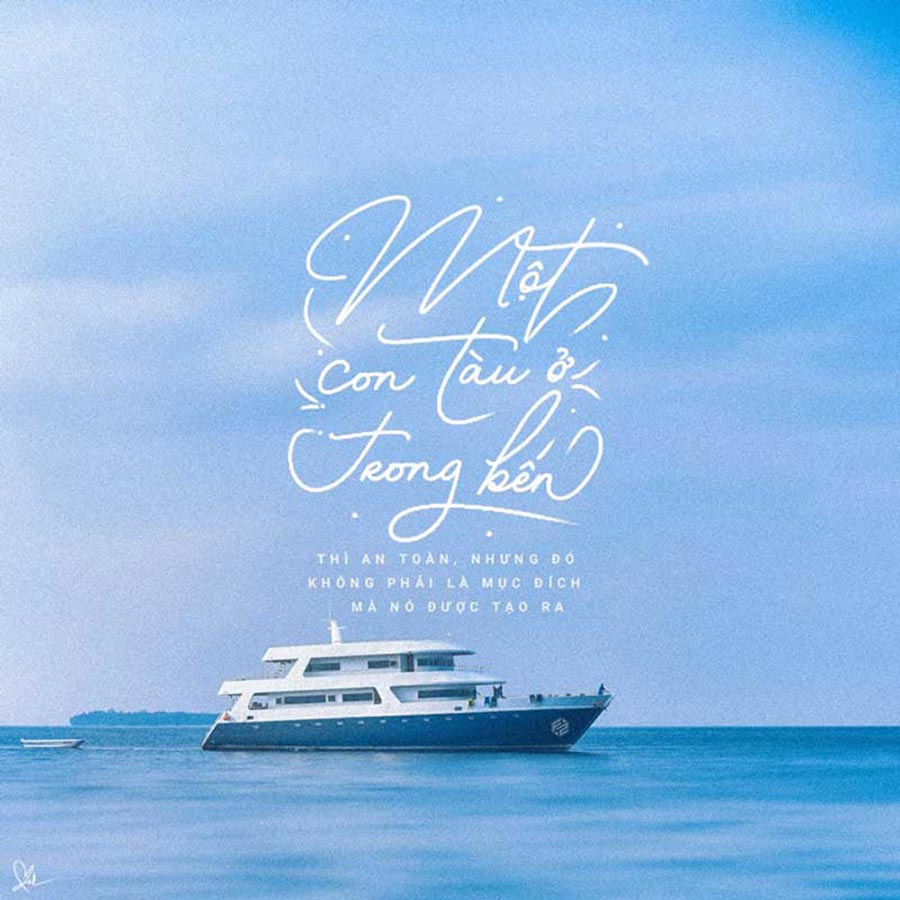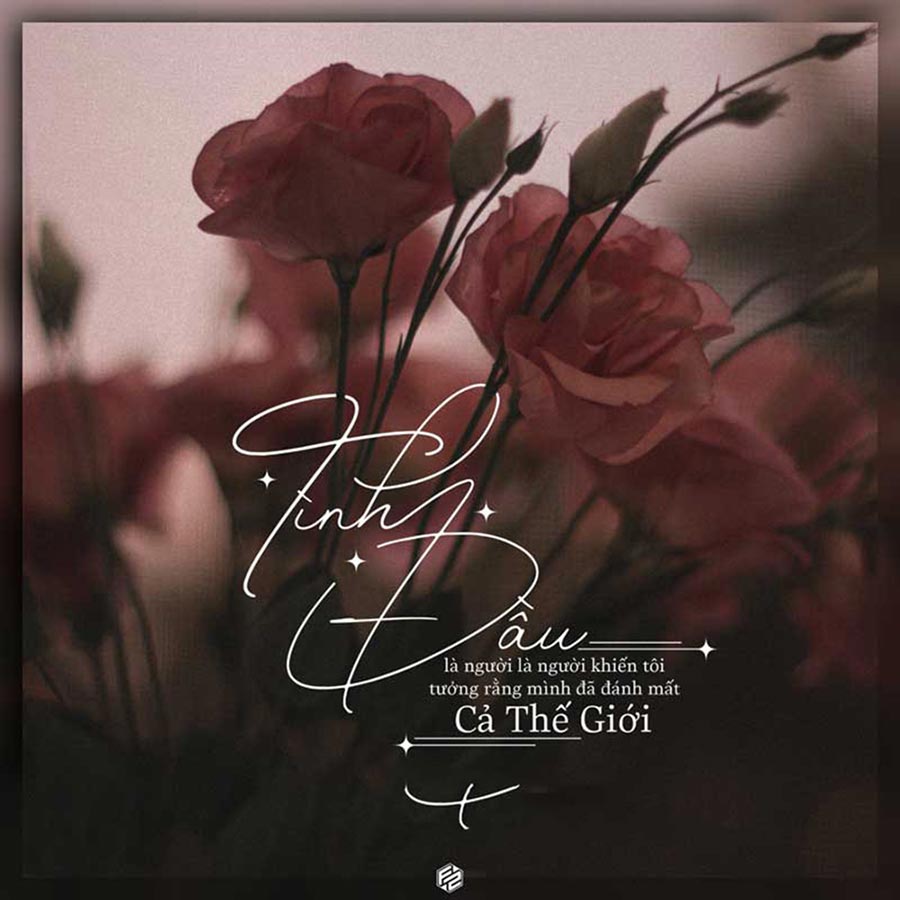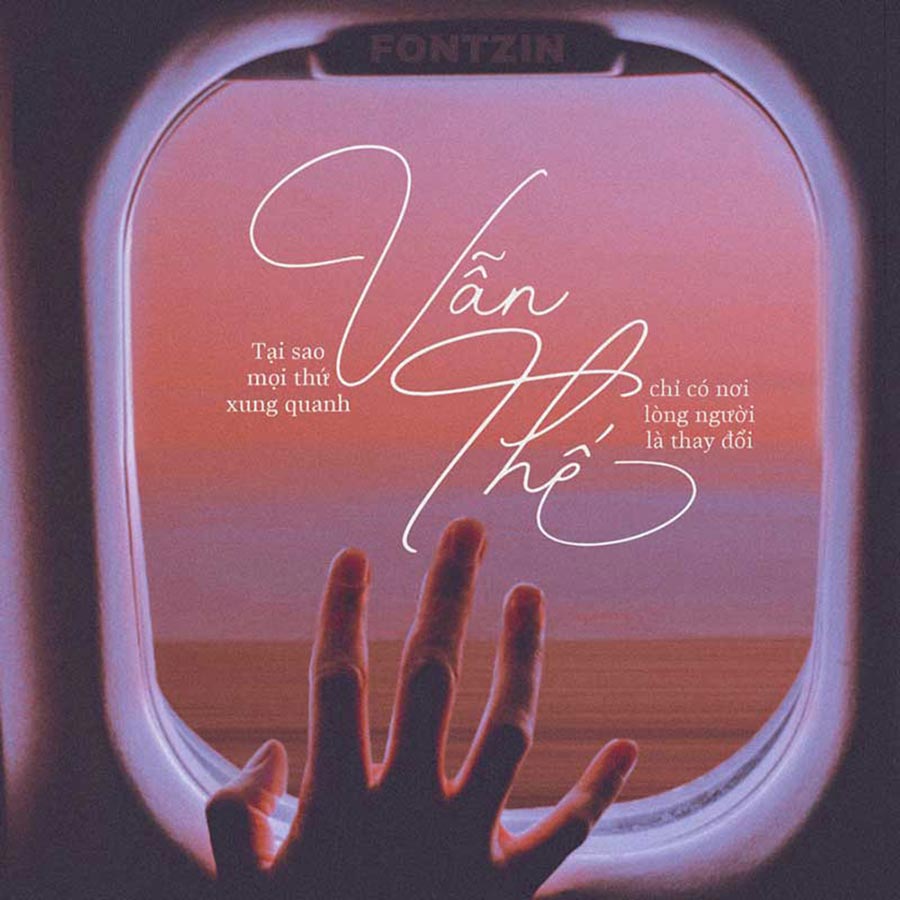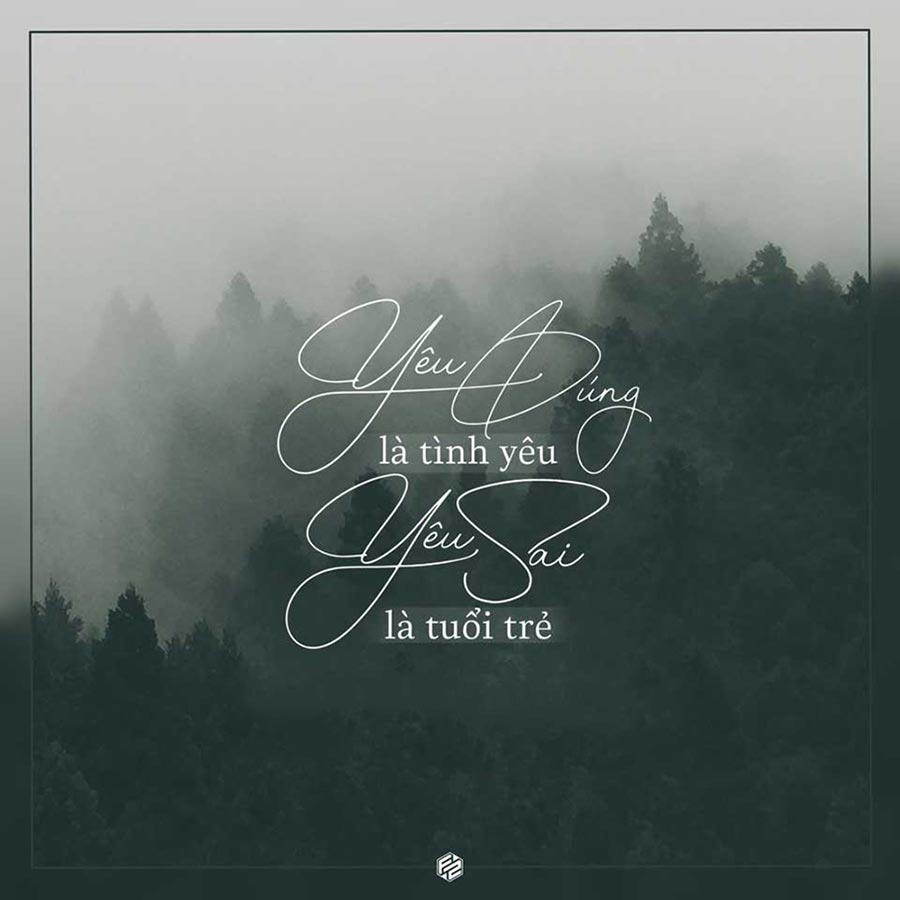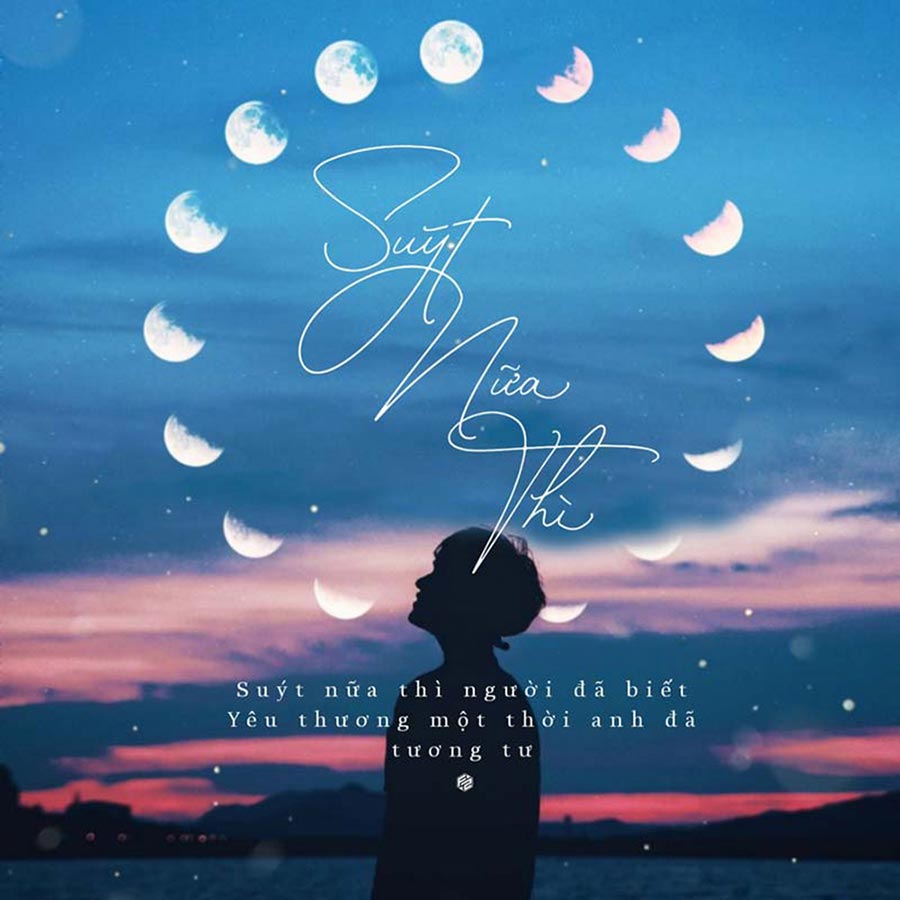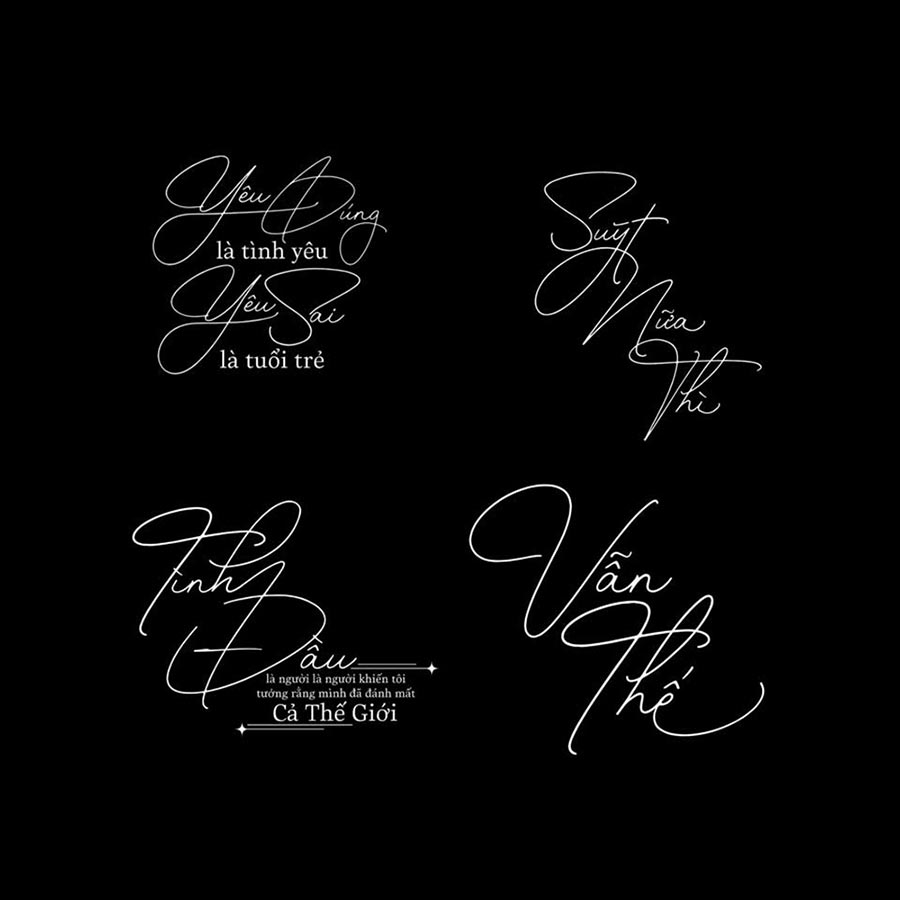
Chia Sẻ Miễn Phí Font Việt Hóa - The Handwritten Watermark Font Chữ Ký Siêu Đẹp
Trong thiết kế đồ họa, việc lựa chọn font chữ là một yếu tố quan trọng, giúp định hình phong cách và truyền tải thông điệp hiệu quả. The Handwritten Watermark Font là một font chữ mang đậm dấu ấn cá nhân, với vẻ đẹp mềm mại và tinh tế, tạo cảm giác như những chữ ký tay chân thực. Đặc biệt, phiên bản Việt hóa của font chữ này đã được chia sẻ miễn phí cho cộng đồng thiết kế, mang đến cơ hội cho mọi nhà thiết kế, từ những người mới bắt đầu đến các chuyên gia, sở hữu một công cụ tuyệt vời để nâng cao chất lượng công việc sáng tạo của mình.
1. Phong Cách Chữ Ký Tinh Tế và Sang Trọng
Font The Handwritten Watermark Font được thiết kế với phong cách chữ ký tự nhiên, mềm mại và tinh tế, giống như nét chữ được viết tay trên giấy. Với các đường cong uyển chuyển và sự kết hợp giữa các ký tự thanh thoát, font chữ này mang lại cảm giác sang trọng và độc đáo. Nó rất phù hợp cho các thiết kế cần sự tinh tế, như thiệp cưới, chữ ký số, logo thương hiệu, và các dự án thiết kế cá nhân hóa. Sự mềm mại của các nét chữ sẽ giúp các sản phẩm thiết kế trở nên gần gũi, lãng mạn nhưng không kém phần trang nhã.
2. Việt Hóa Hoàn Hảo Cho Dự Án Thiết Kế Tiếng Việt
Một trong những điểm đáng chú ý của The Handwritten Watermark Font là phiên bản Việt hóa hoàn hảo. Các ký tự và dấu tiếng Việt đã được tích hợp đầy đủ, giúp người dùng thiết kế dễ dàng sử dụng font này cho các dự án văn bản tiếng Việt mà không gặp phải vấn đề thiếu sót. Với các nhà thiết kế Việt Nam, điều này rất quan trọng bởi nó giúp đảm bảo tính chính xác trong việc hiển thị ngôn ngữ và mang lại sự đồng nhất trong toàn bộ thiết kế. Font chữ này sẽ giúp các tác phẩm thiết kế của bạn trở nên ấn tượng và dễ tiếp cận hơn với người xem Việt Nam.